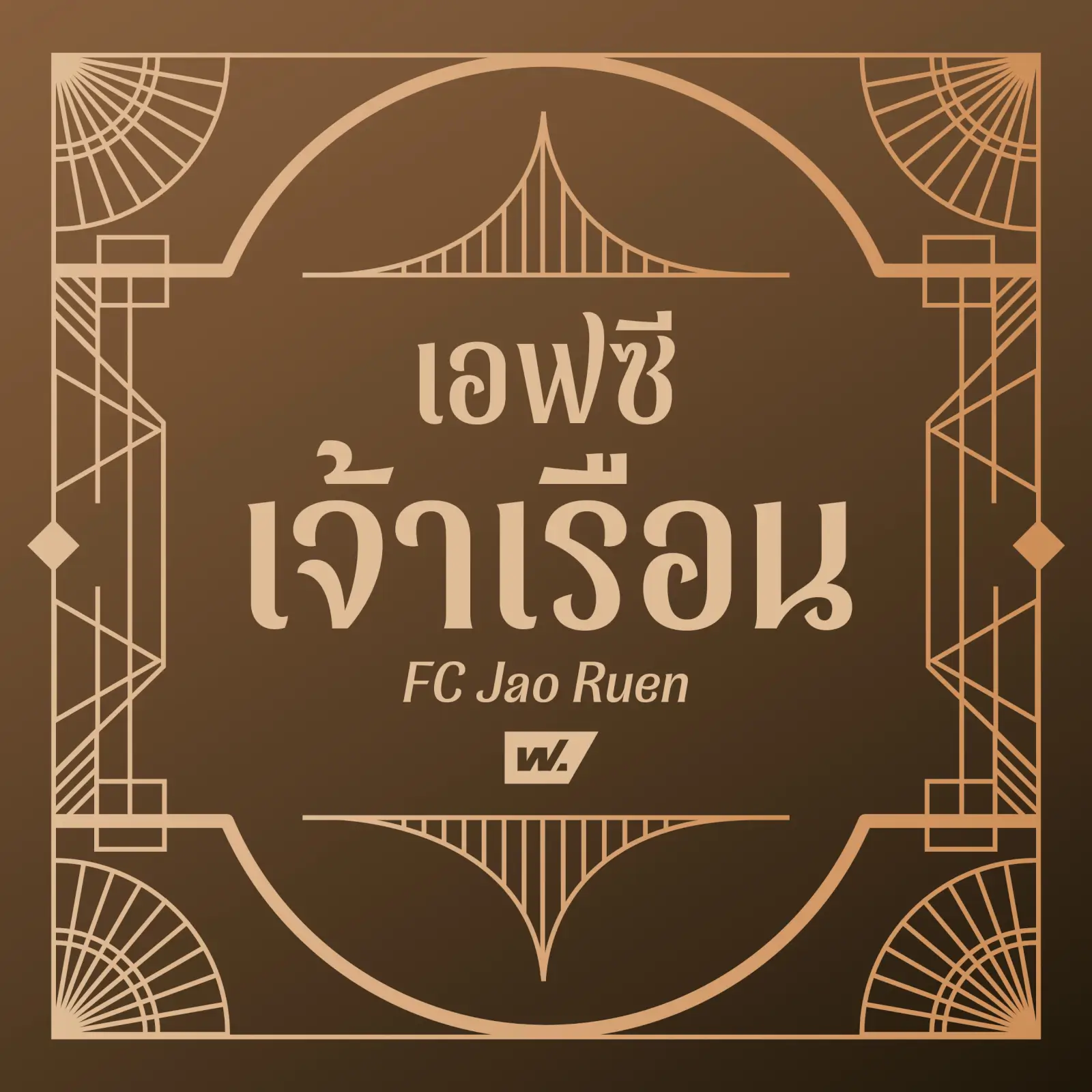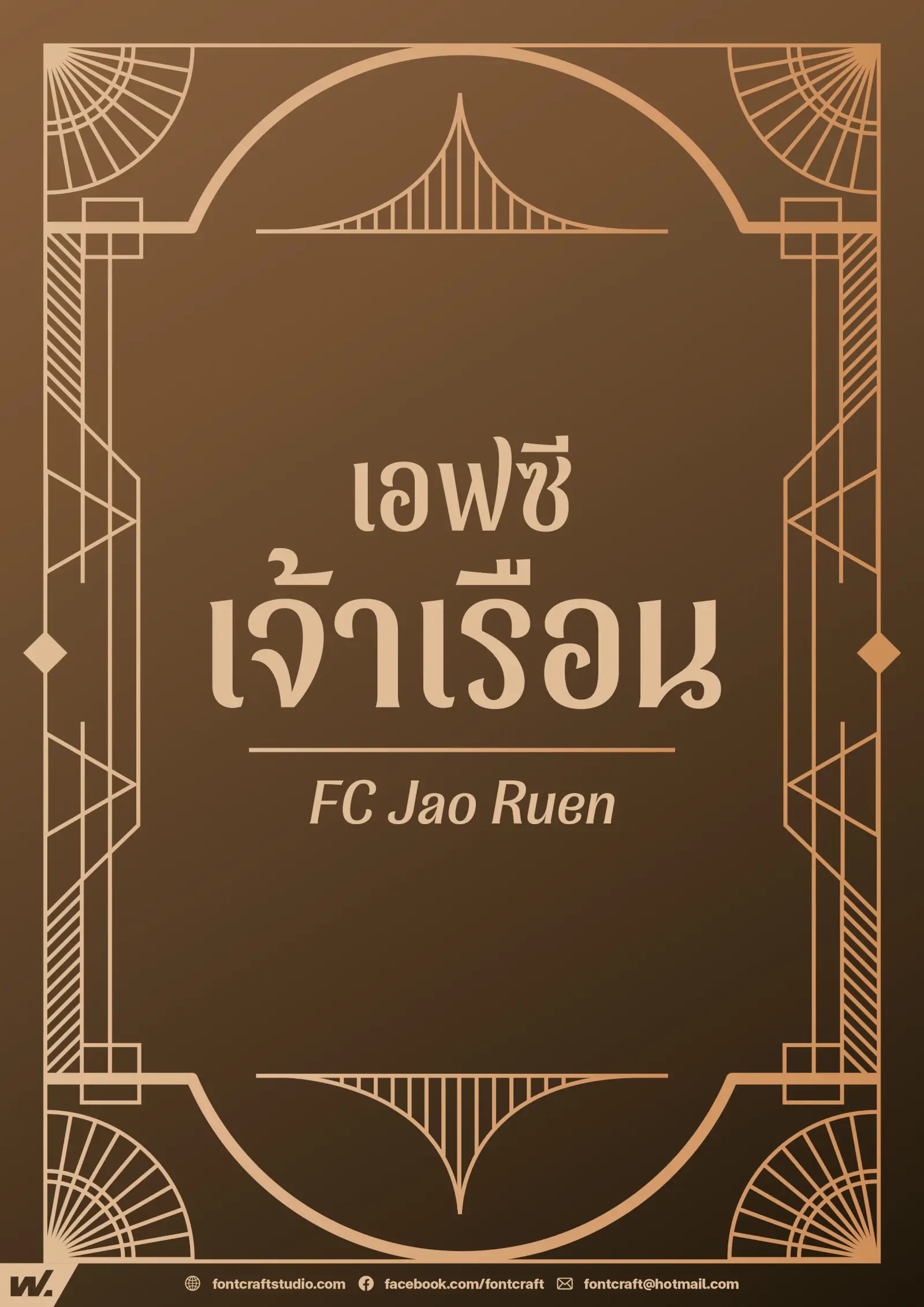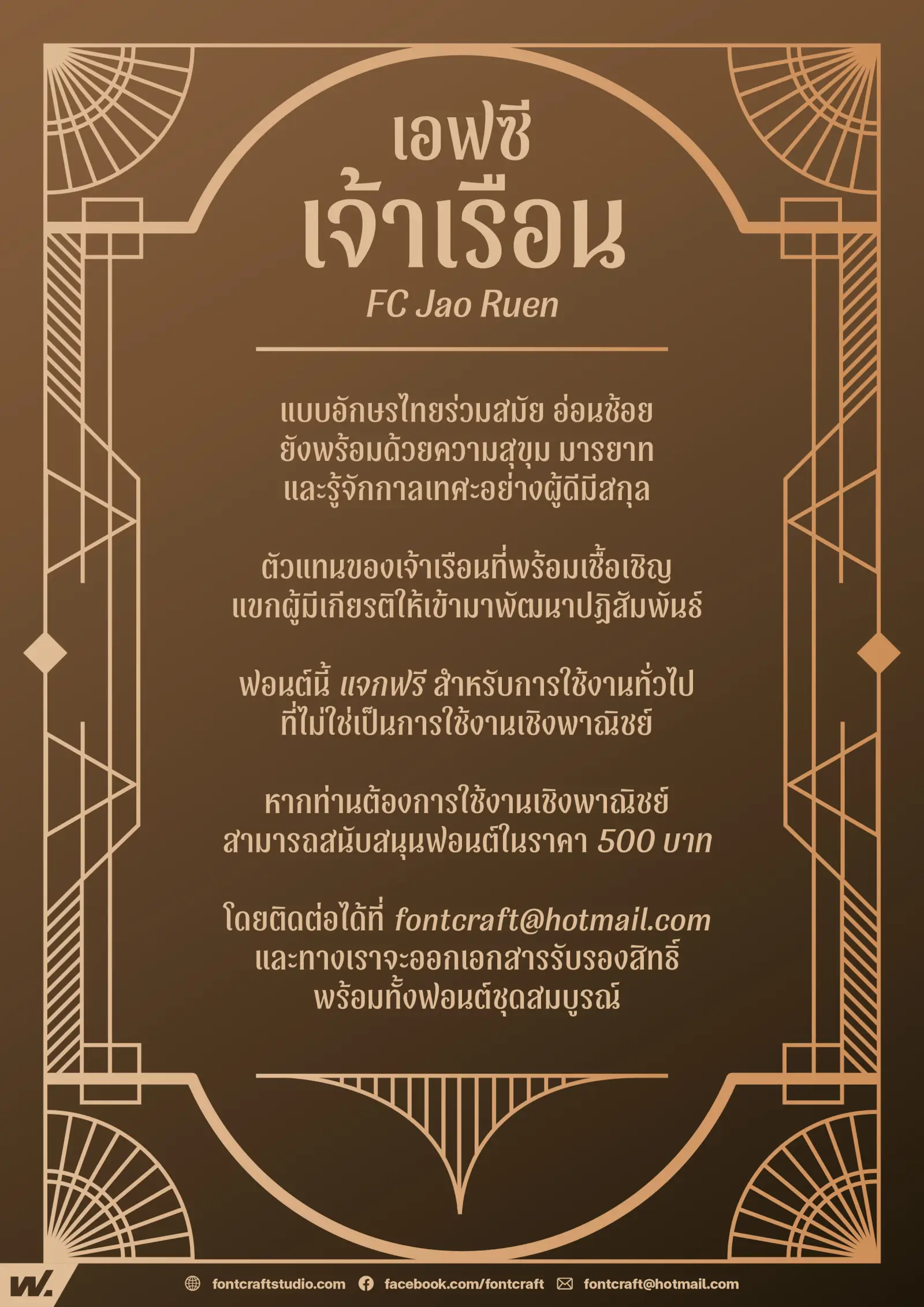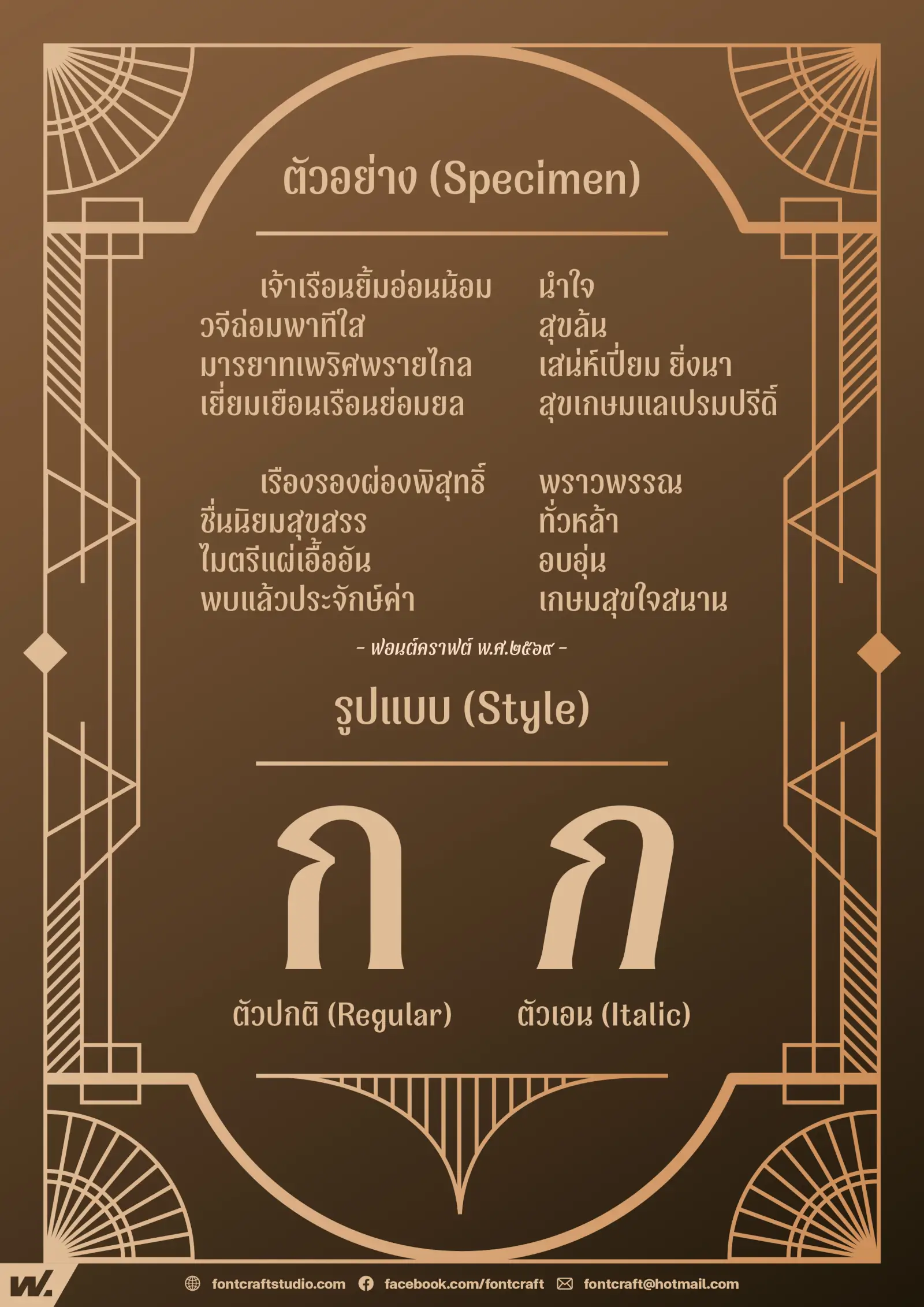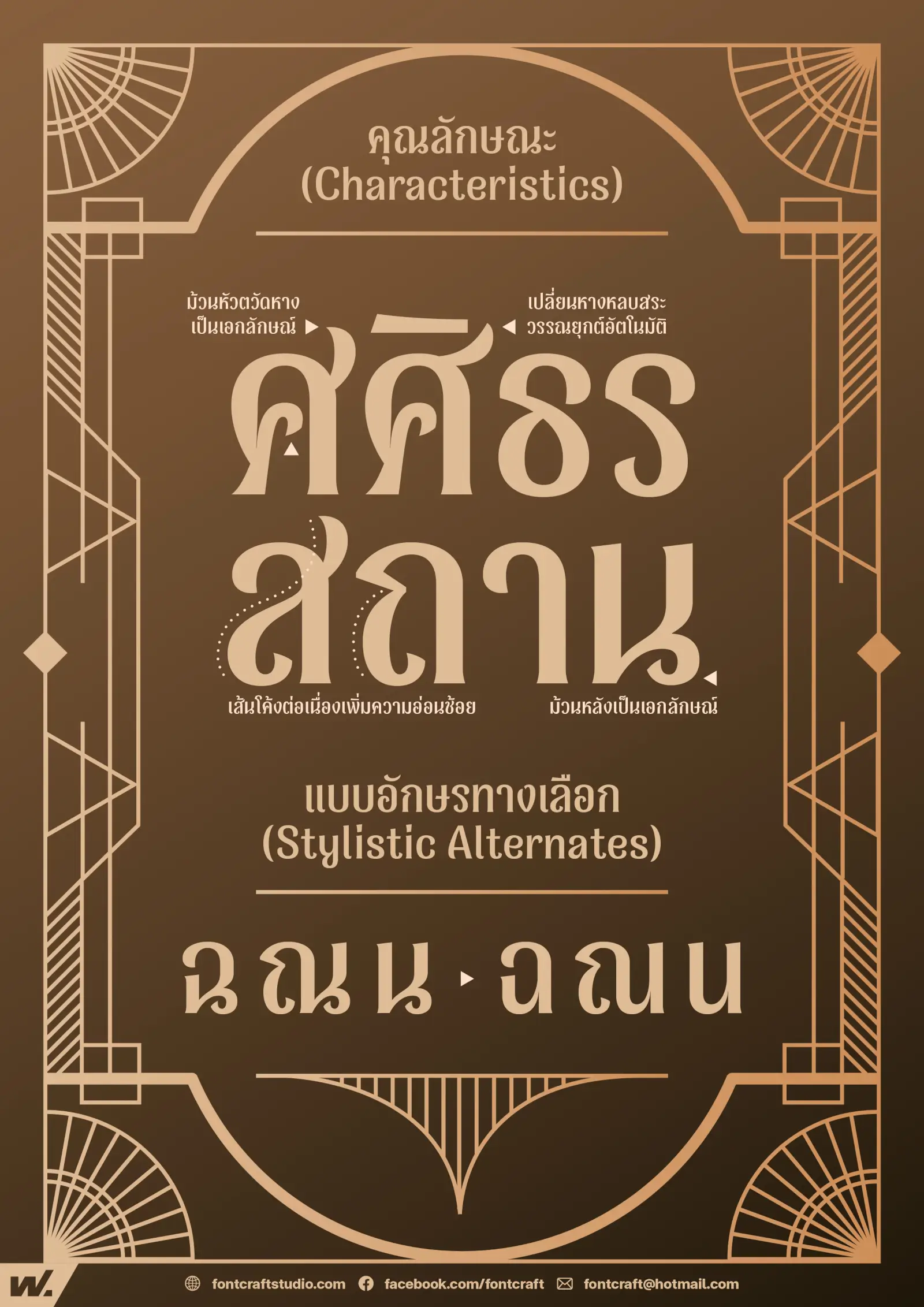
แบบอักษรไทยร่วมสมัย อ่อนช้อย ยังพร้อมด้วยความสุขุม มารยาท และรู้จักกาลเทศะอย่างผู้ดีมีสกุล อันเป็นตัวแทนของเจ้าเรือนที่พร้อมเชื้อเชิญแขกผู้มีเกียรติให้เข้ามาพัฒนาปฏิสัมพันธ์
โครงสร้างม้วนหัวตวัดหางเป็นเอกลักษณ์ ตัวอักษรอ่อนช้อย แทรกฟีเจอร์ที่ตัวอักษรจะเปลี่ยนหางหลบสระ-วรรณยุกต์โดยอัตโนมัติ และมีตัวอักษรทางเลือก Stylistic Alternates (ss01) เลือกม้วน-ไม่ม้วนหัวด้านหลังของตัวอักษรกลุ่ม น หนู
เหมาะสำหรับงานที่ต้องการสื่อถึงความเป็นไทย ทั้งด้านอาหาร การท่องเที่ยว ศาสนา สินค้าและบริการของไทย